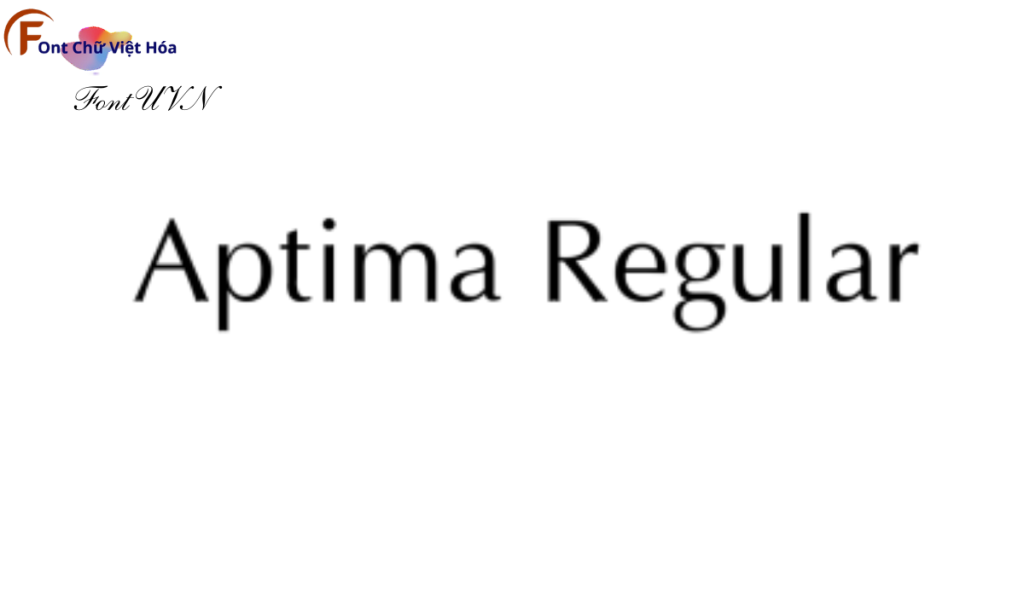
Font Aptima UVN Việt Hóa
Ngôn ngữ: Tiếng Việt, Latin, Số
Bộ Font: UVN
Phân loại: Thanh lịch, hiện đại
Độ dày: Mỏng, Thường, Đậm
Font Aptima UVN Việt Hóa là một font chữ không chân hiện đại, thuộc bộ font UVN. Được thiết kế với mục tiêu mang lại sự tinh tế và thanh lịch, font này phù hợp cho các dự án thiết kế như website, tài liệu, và bao bì sản phẩm. Với các nét chữ rõ ràng và độ dày đều đặn, Font Aptima UVN Việt Hóa không chỉ dễ đọc mà còn tạo cảm giác chuyên nghiệp. Việc Việt hóa font giúp người dùng dễ dàng sử dụng trong các thiết kế tiếng Việt, mang lại sự tiện lợi và thẩm mỹ cao.